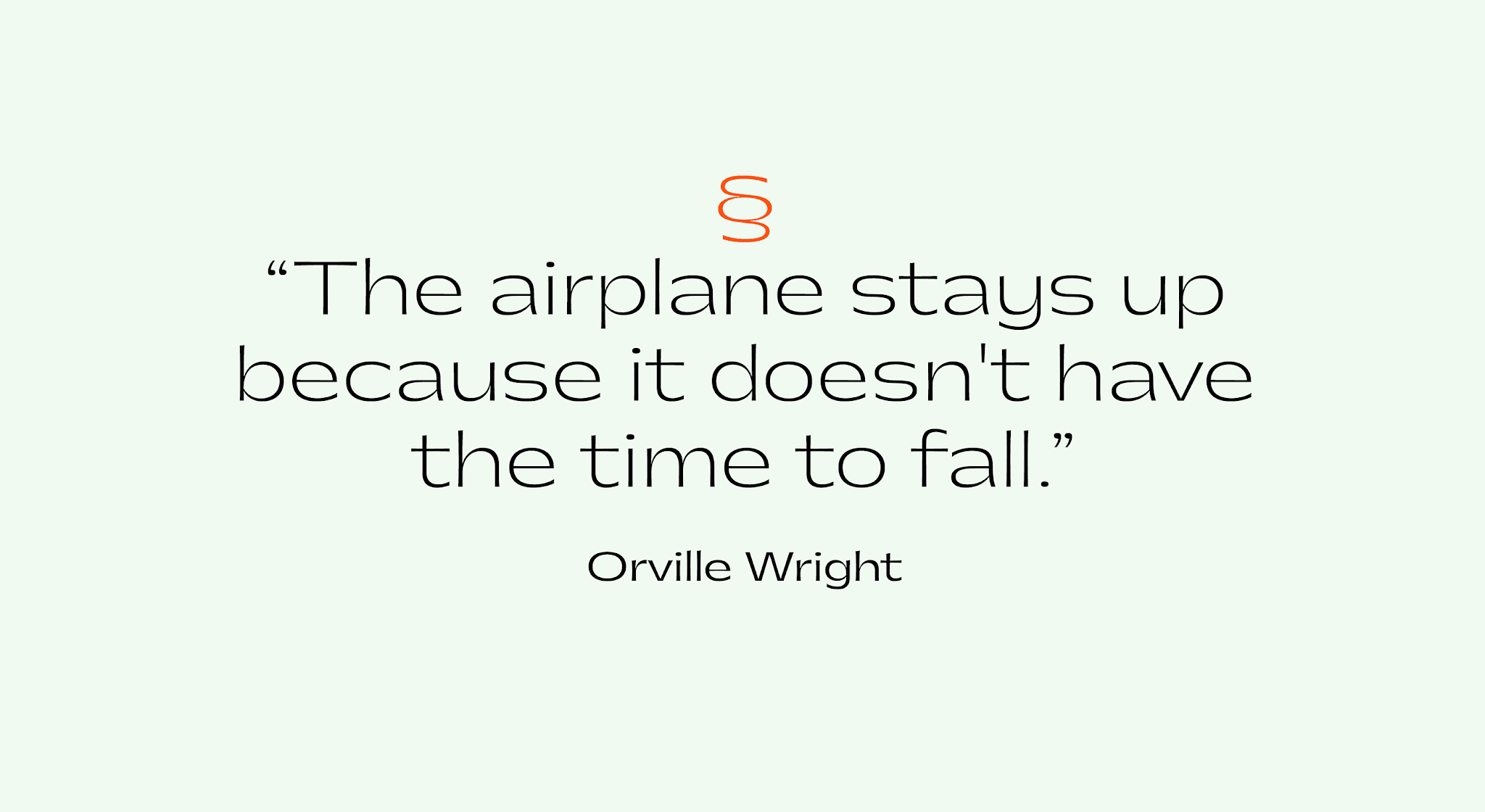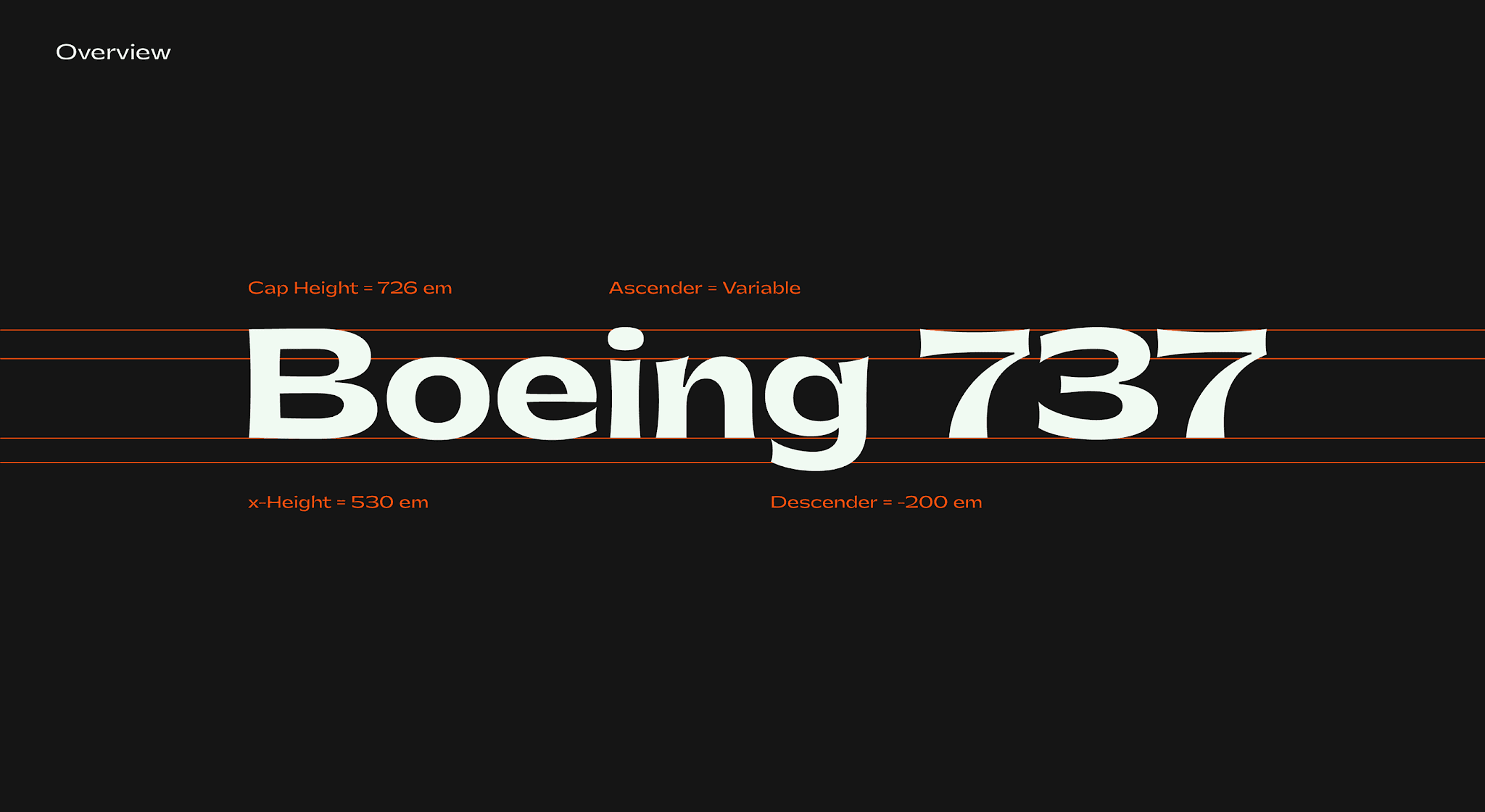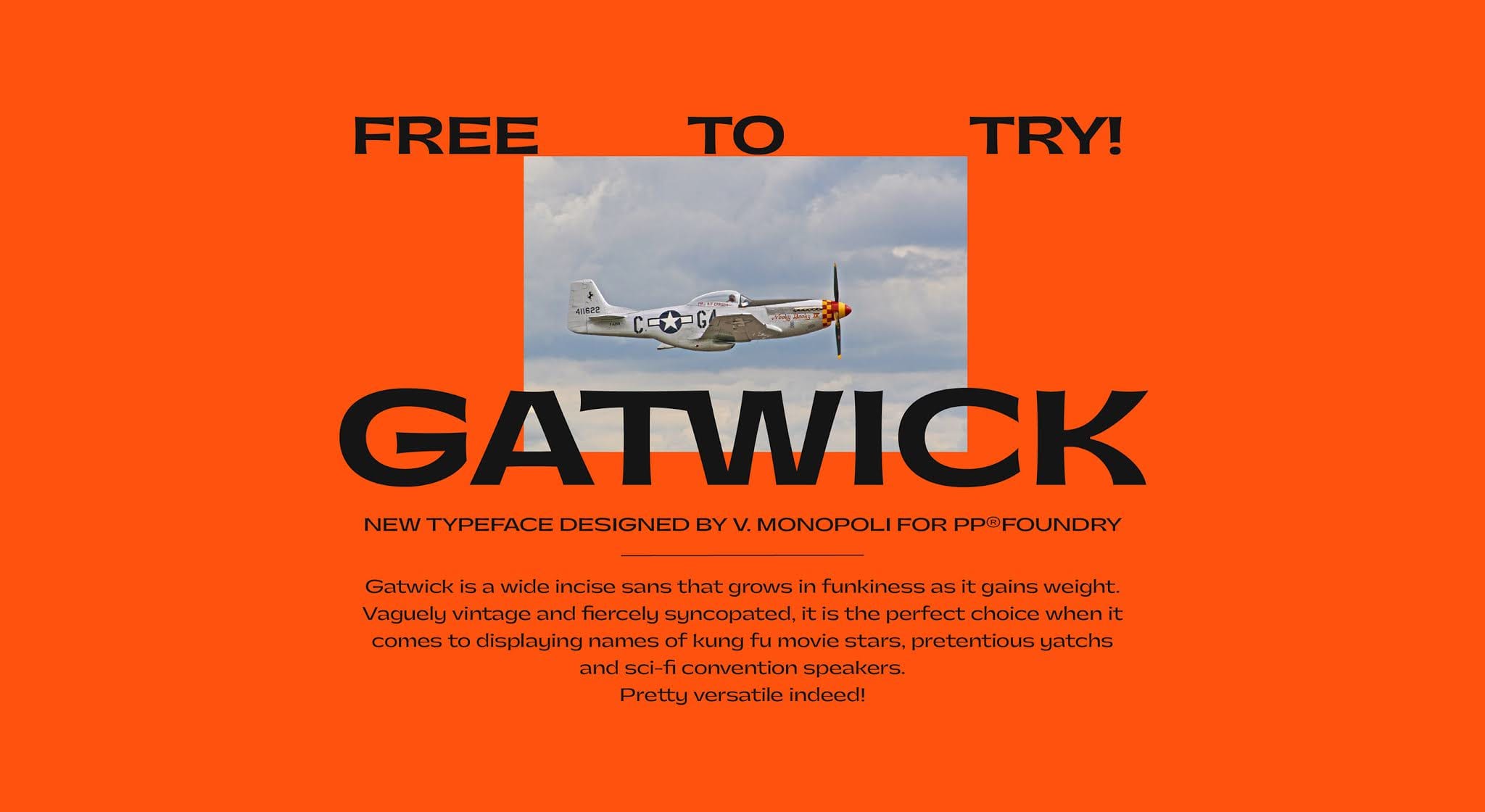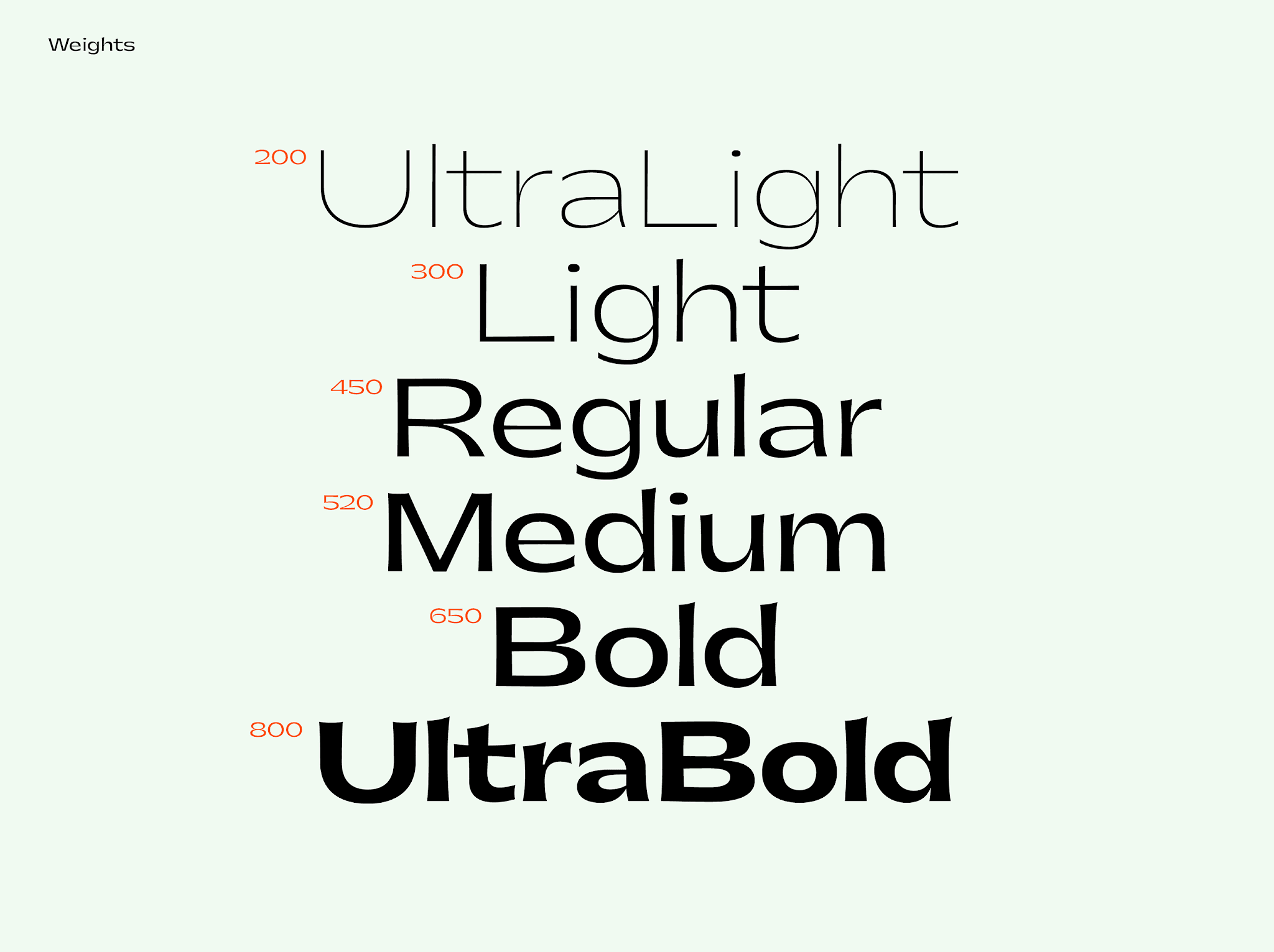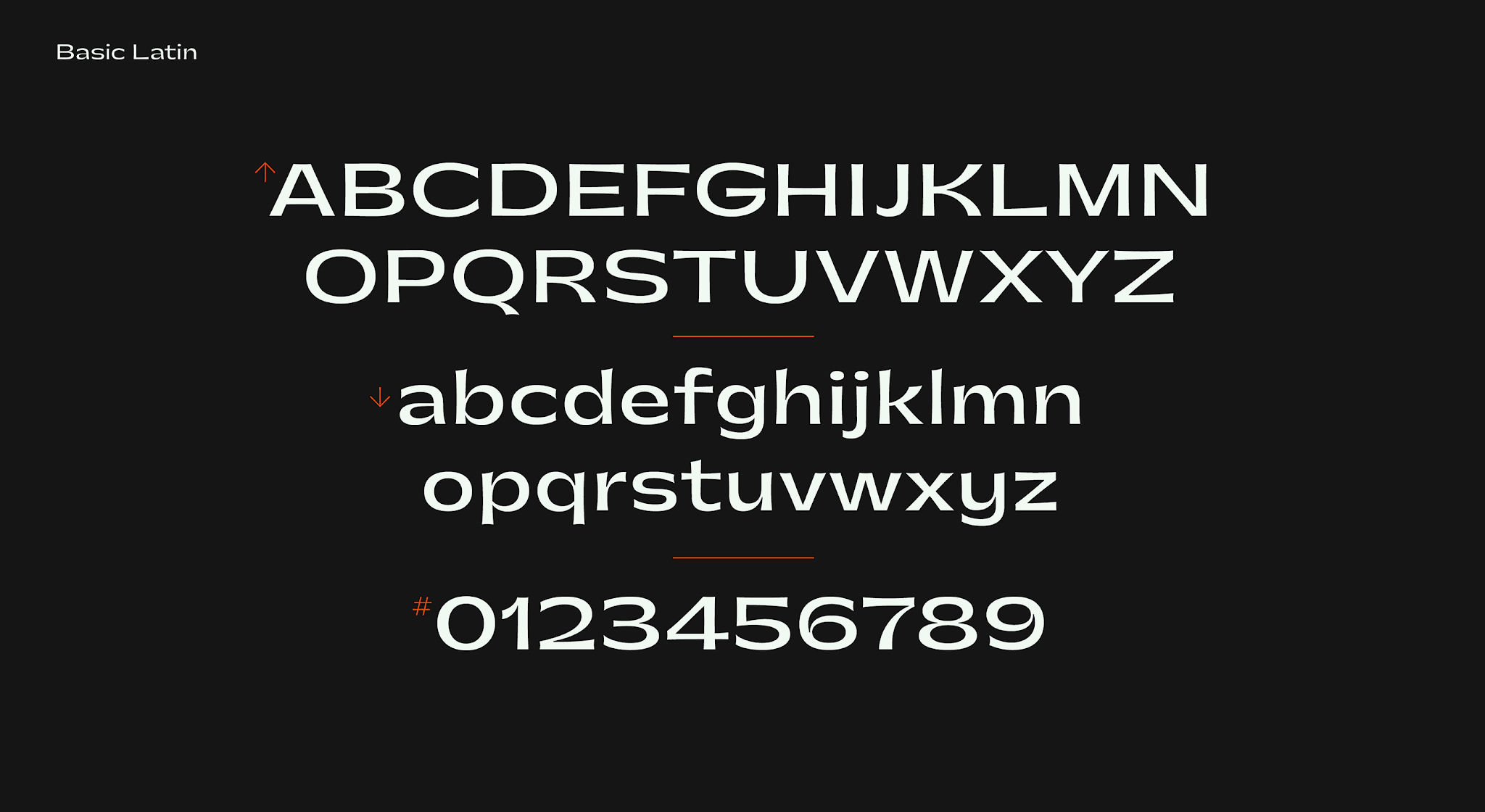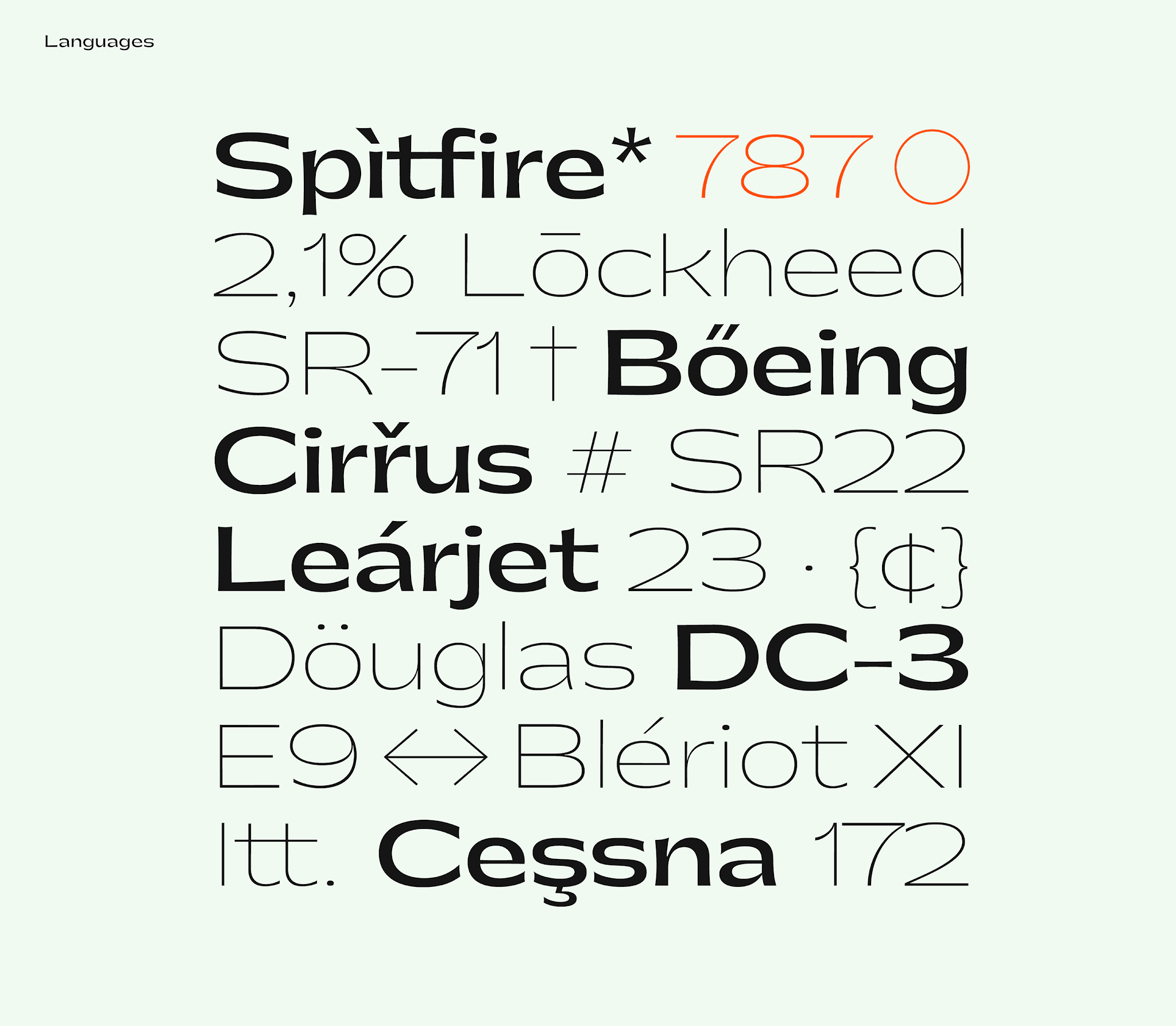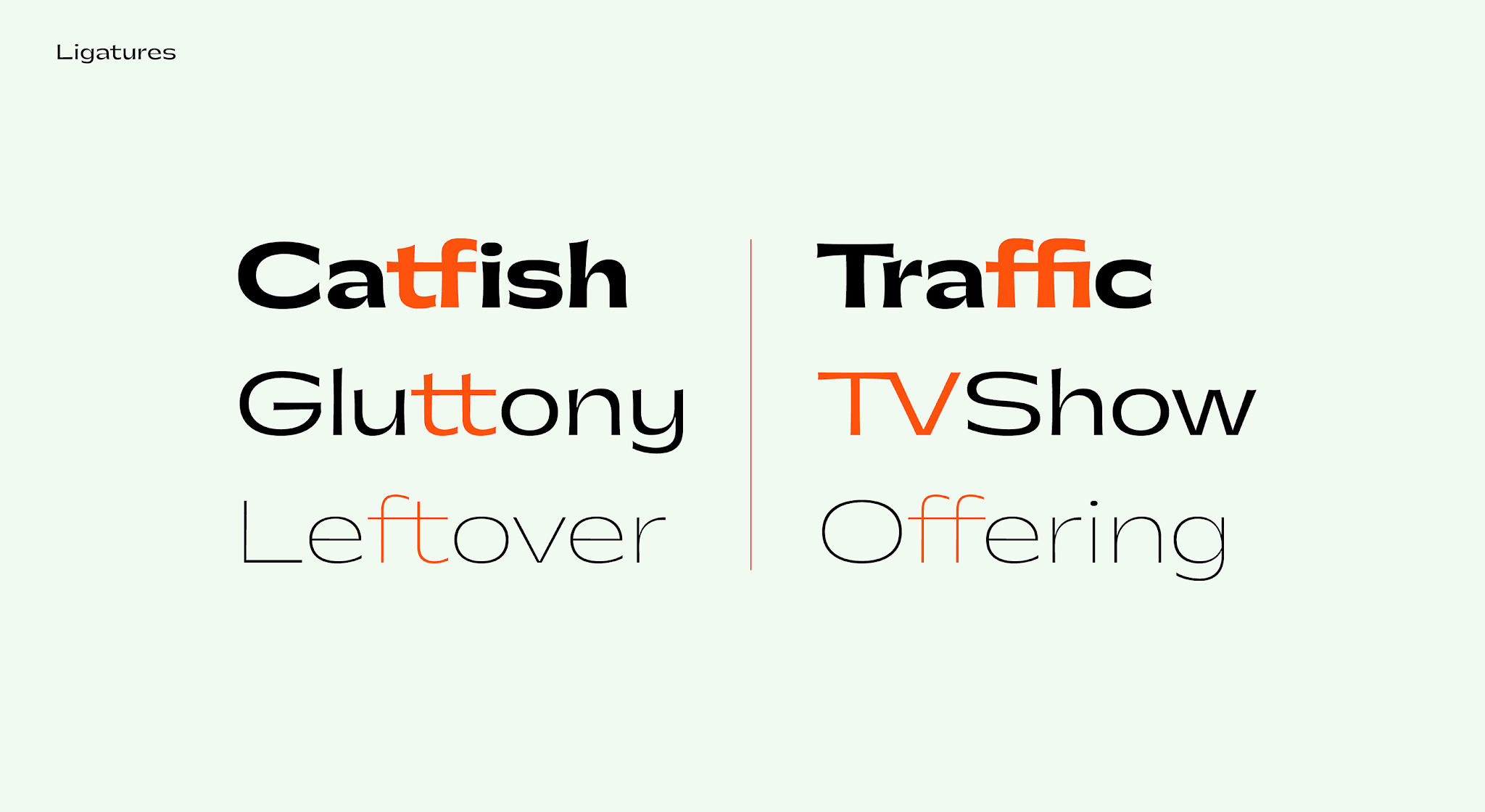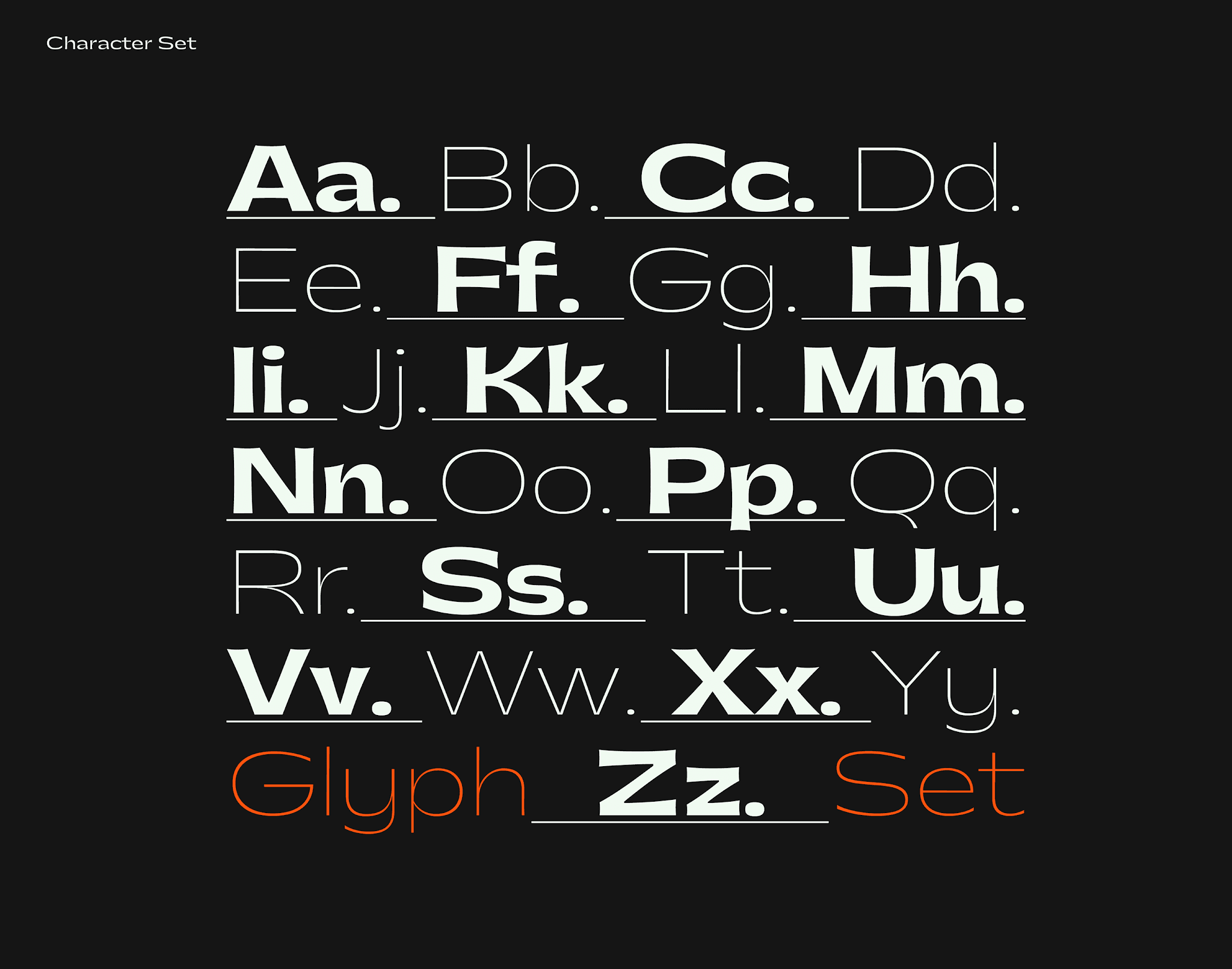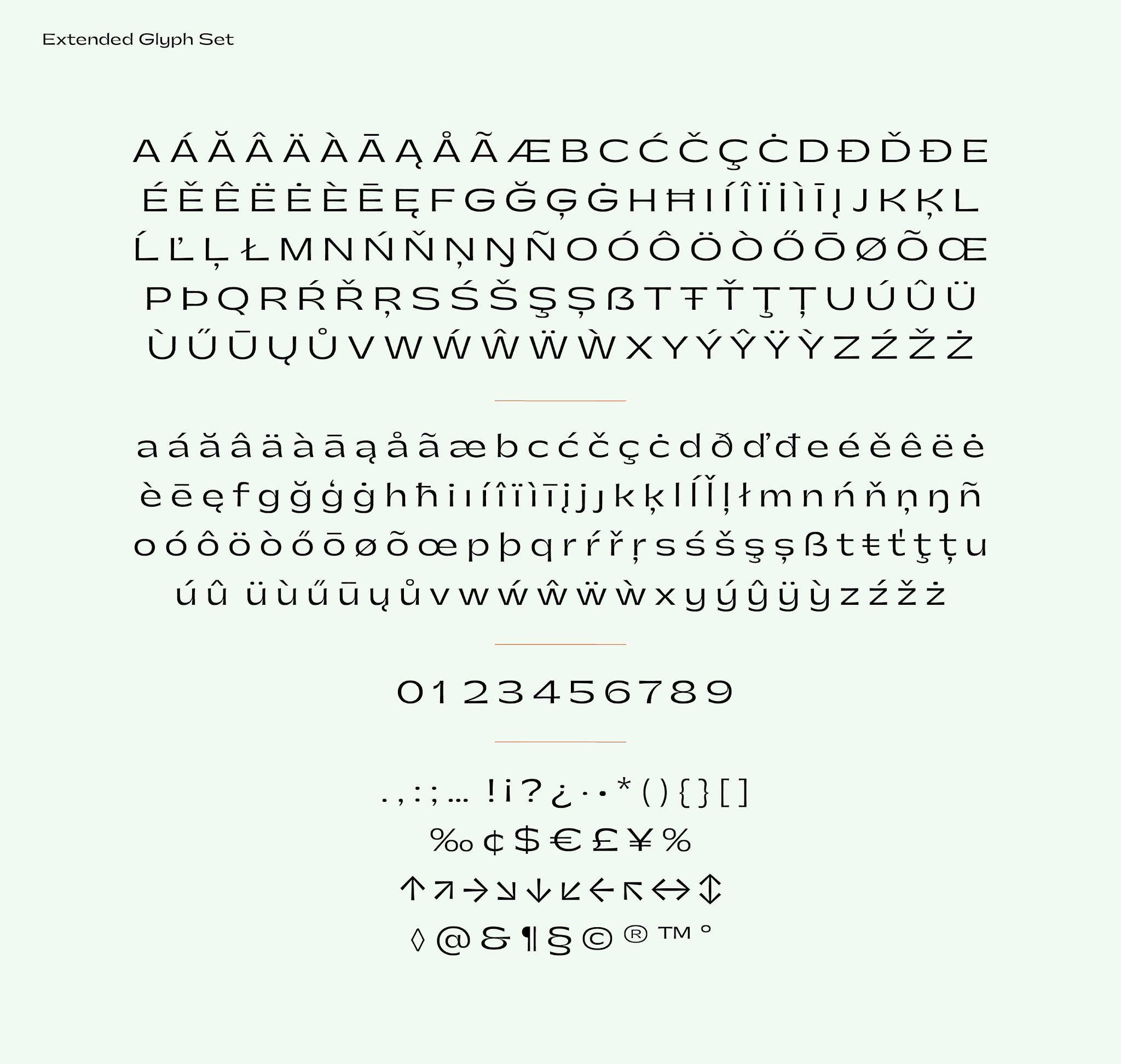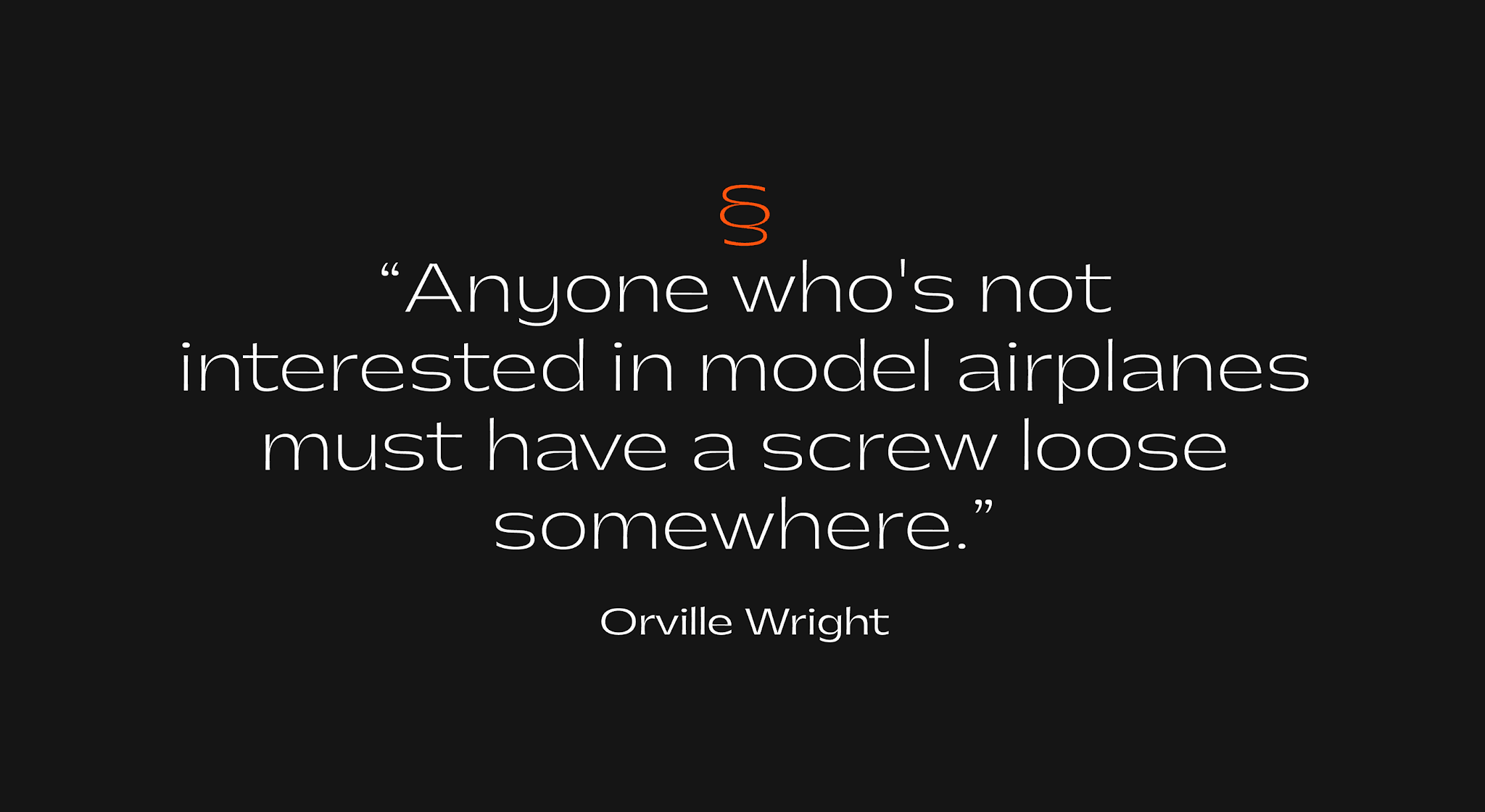
Gatwick là một bộ font chữ ấn tượng với các thiết kế dài mang hơi hướng cổ điển và đồng bộ dữ dội, đây là sự lựa chọn hoàn hảo khi
trưng bày tên các ngôi sao điện ảnh kung fu, du thuyền kiêu kỳ và loa hội nghị khoa học viễn tưởng.
Gatwick Font Family bao gồm 6 style với 378 glyph mỗi kiểu. Hỗ trợ ngôn ngữ cho Châu Mỹ và hầu hết Châu Âu.